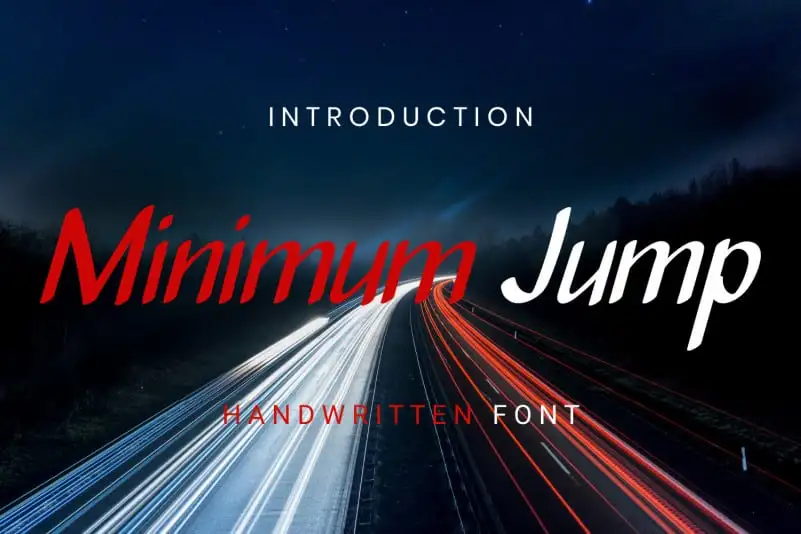
Minimum Jump Handwritten Font – Download Grátis
A “Minimum Jump Handwritten Font” é uma fonte escrita a mão que transmite uma sensação de simplicidade encantadora. Suas linhas levemente relaxadas e sua natureza amigável a tornam perfeita para diversos estilos de design, tornando-a um complemento ideal para suas ideias criativas. Descubra como essa fonte pode transformar seus projetos em algo vivido, real e cheio de vida. Essa fonte é uma escolha inteligente para quem busca simplicidade e elegância em cada projeto visual. Adicione essa fonte a seu arsenal de ferramentas gráficas e veja como ela faz a diferença no design do qual gosta!